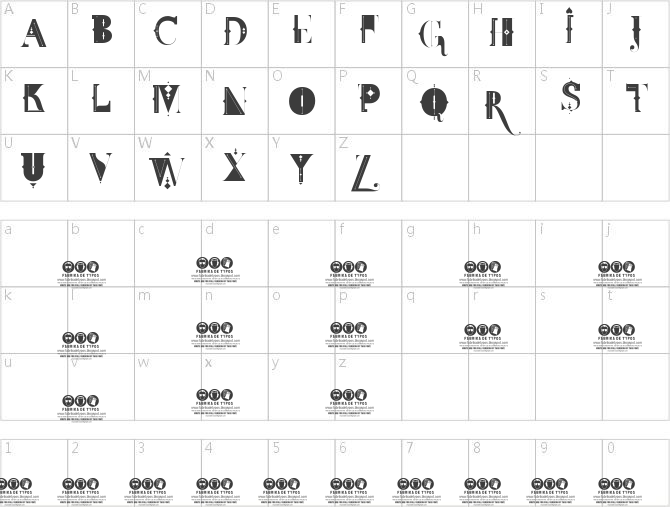
FDT_Wonderland_DEMO_VERSION
FDT_Wonderland_DEMO_VERSION介绍
FDT_Wonderland_DEMO_VERSION字体字库是一款让人赏心悦目、百看不厌的英文字体,适合各类广告和产品包装设计应用,字体大小0.41MB,格式为ttf字体,上传用户是翰池书法,作者/版权方为未知